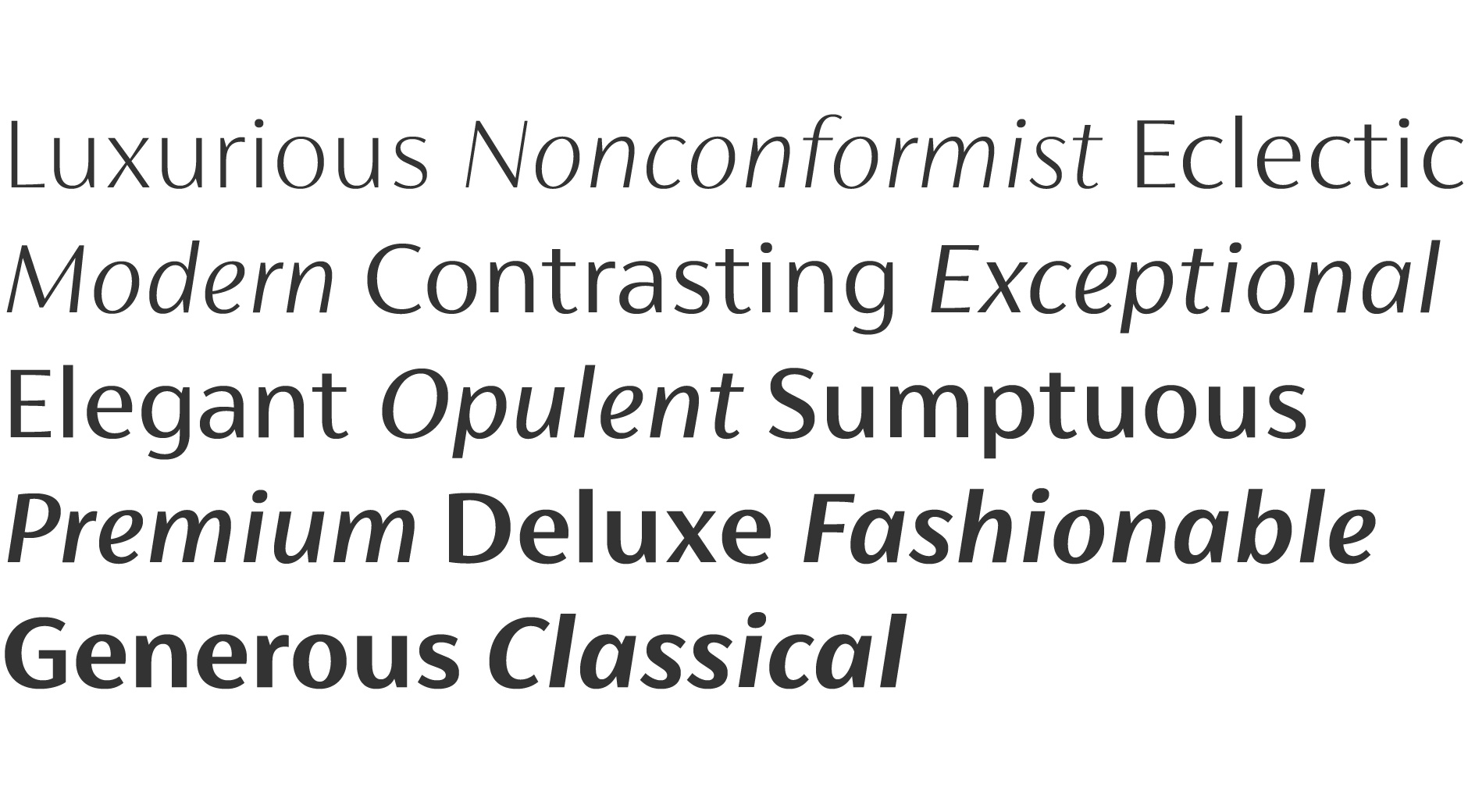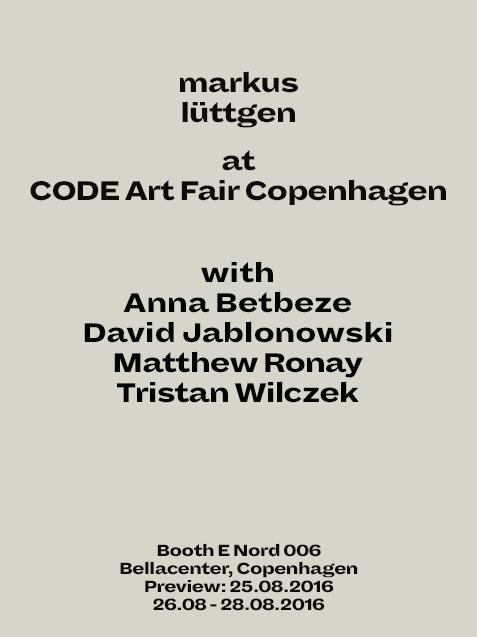
Empfehlungen kontraststarke Serifenlose ?
Ich würde gerne eine konstraststarke Serifenlose verwenden, möglichst mit zweistöckigem a und vielleicht auch dreistöckigem g, ansonsten aber näher an Akzidenz, Helvetica etc. als etwa die Franklin Gothik oder Bell Gothic es sind. Hätte da jemand eine oder zwei Ideen?
Hallo, vielen Dank für eure Vorschläge. Ich habe noch ein wenig gesucht … und dachte eigentlich eher an etwas der Art wie hier im Anhang. Keine Ahnung was das ist. Ideen in der Richtung?
Warum nicht? Die Strichstärkenunterschiede – a, e, b, d … – sind doch erheblich. Allerdings, in den Versalien sind sie schwächer als die der Optima.